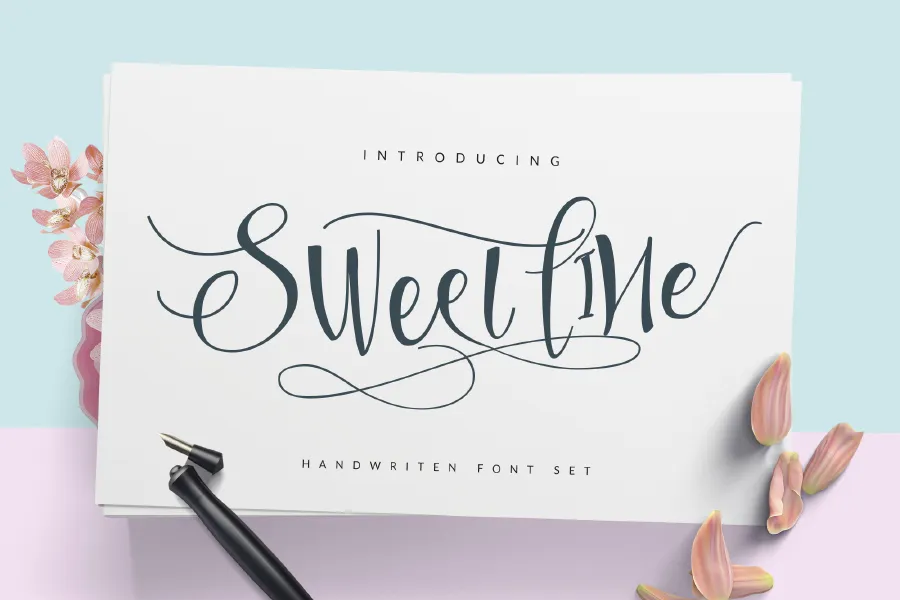
Sweetline Script Font – Download Grátis
A Sweetline Typeface é uma seleção única para designers que buscam unir elegância e modernidade em seu trabalho. Esta tipografia calligráfica traz formas onduladas modernas e clássicas, perfeitamente adaptada para um vasto range de projetos. Seja para criar marcas únicos e inovadores, como logotipos ou ícones digitais, expressar mensagens poderosas em impressões publicitárias, desenhar cartões de agradecimento elegantes, embalagens de produto sofisticadas ou até mesmo cabeçalhos imponentes. A Sweetline Typeface atua como uma ferramenta versátil, permitindo imaginação e criatividade no design dos mais variados tipos de materiais. Com sua estrutura única e fluida, esta fonte é um tesouro para qualquer designer interessado em adicionar sofisticação e personalização aos seus projetos.